今回のバンドルは「多岐に渡る品揃え!満腹フォントコレクション」。クラシックなデザイン書体からトレンド感溢れるおしゃれなディスプレイ書体まで、仕事や趣味が楽しくなること間違いなしのフォントが勢揃い!
「多岐に渡る品揃え!満腹フォントコレクション」の気になる中身をご紹介
ウェイト豊富で骨太な印象のスラブセリフフォント:CORPORATIVE SLAB
正体・イタリック体それぞれに8種類のウェイトを用意したスラブセリフフォント「CORPORATIVE SLAB」。インパクトを残したいポスターやチラシのデザインなどに役立つフォントです。
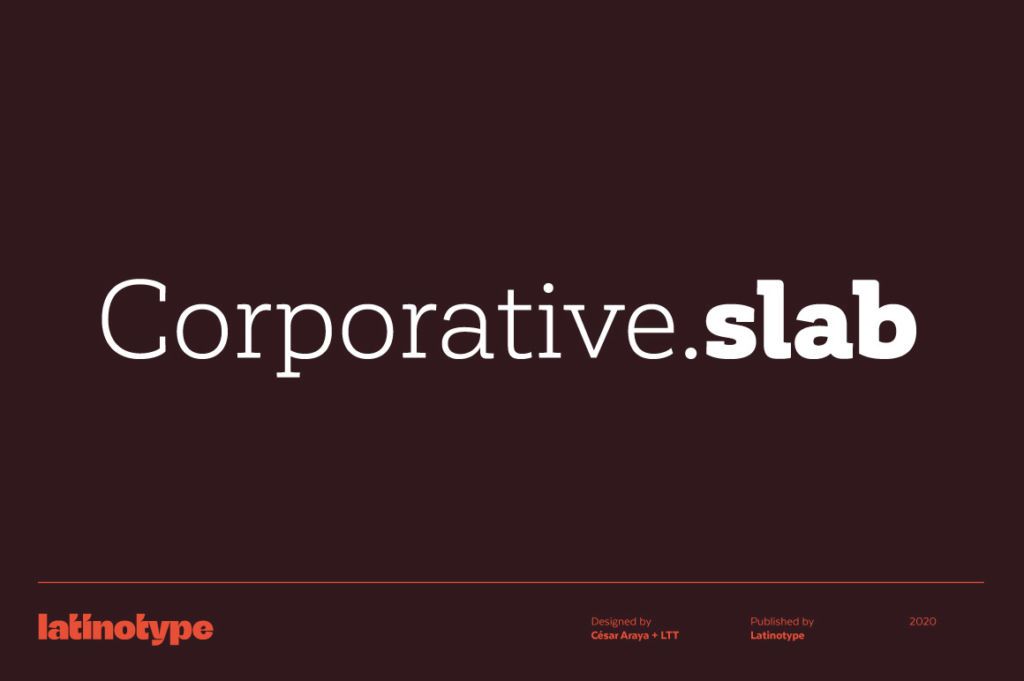
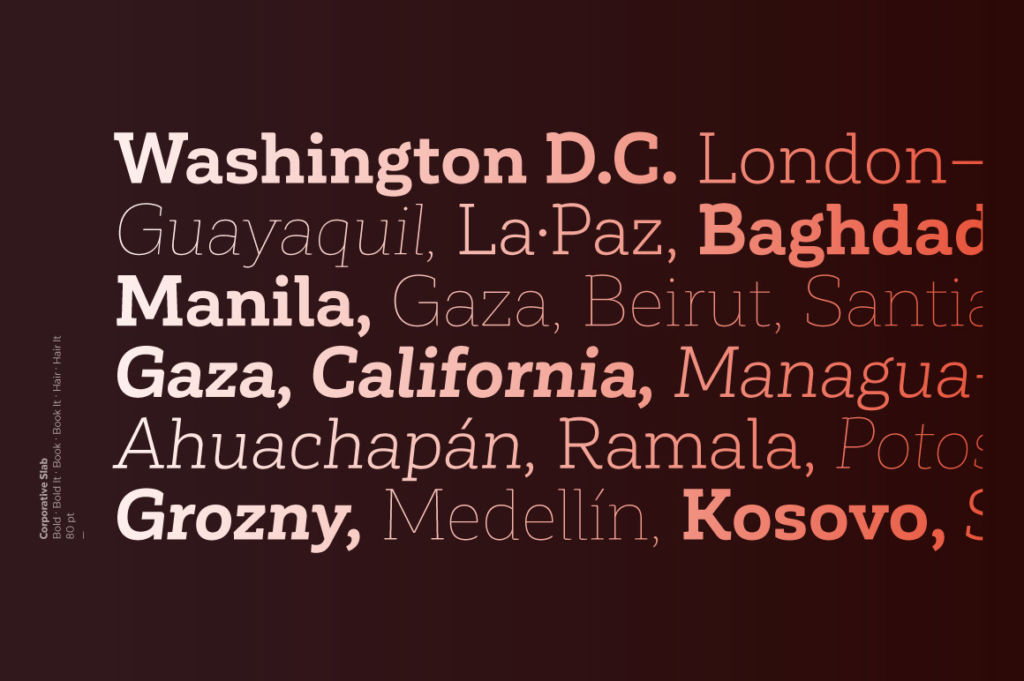
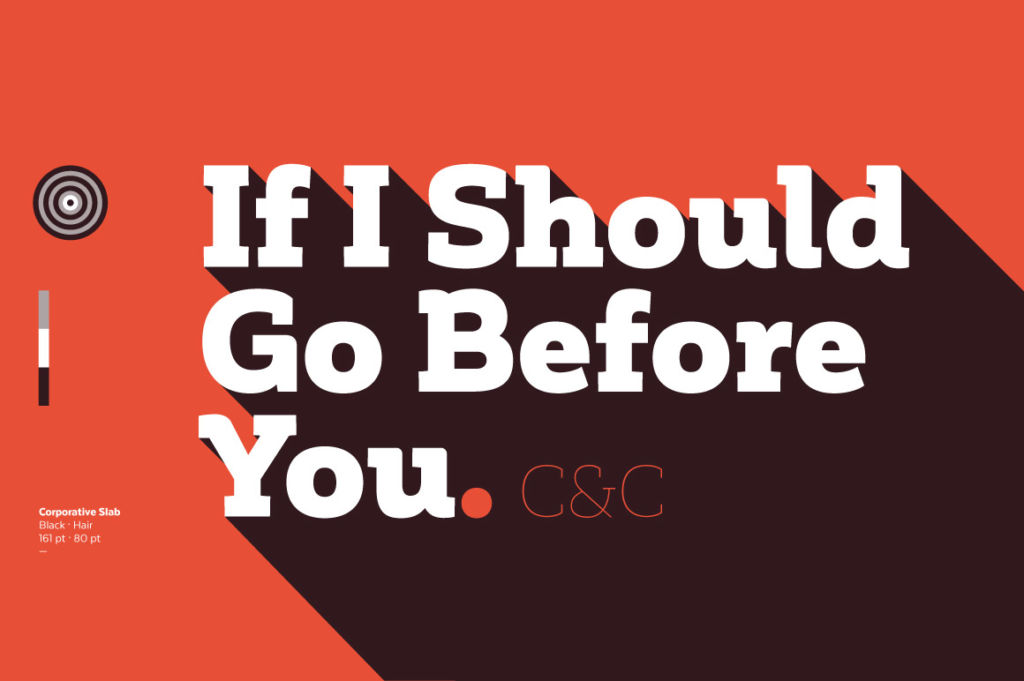
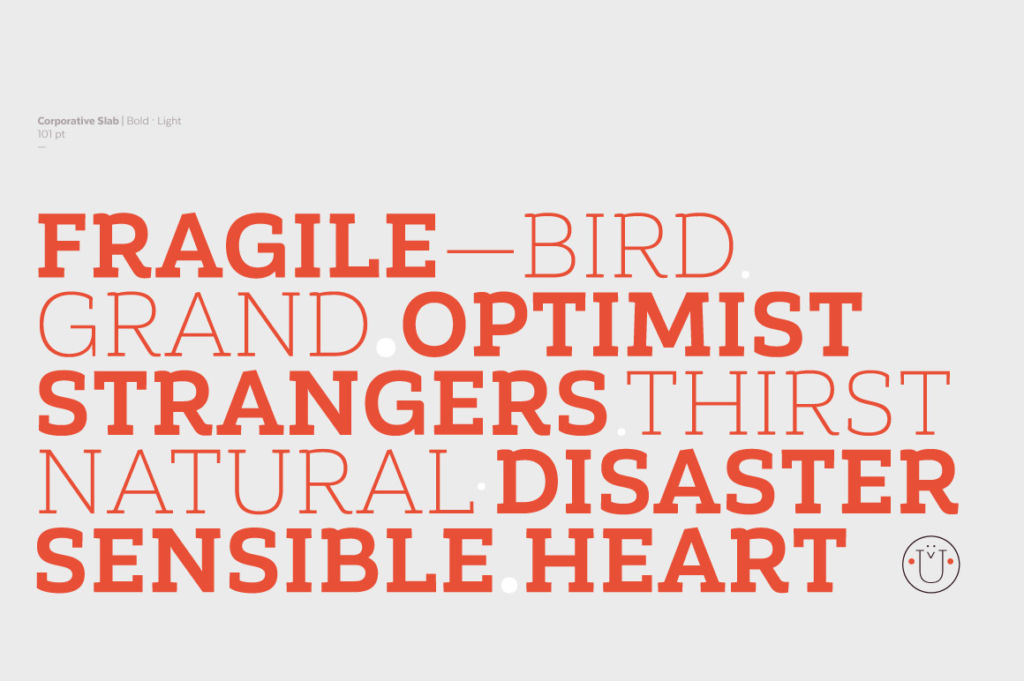
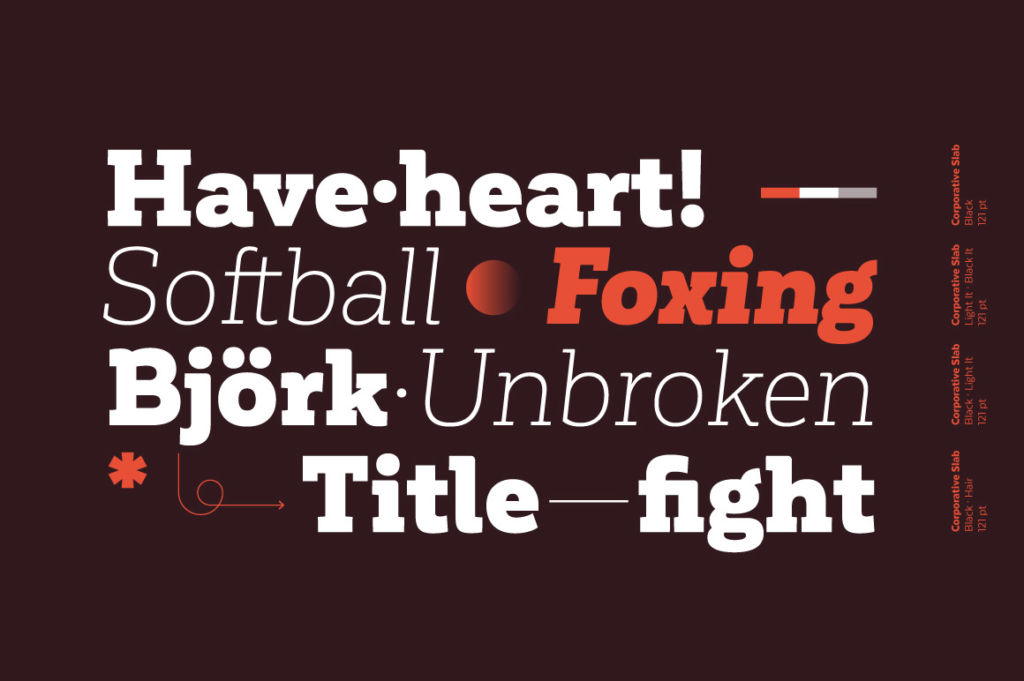
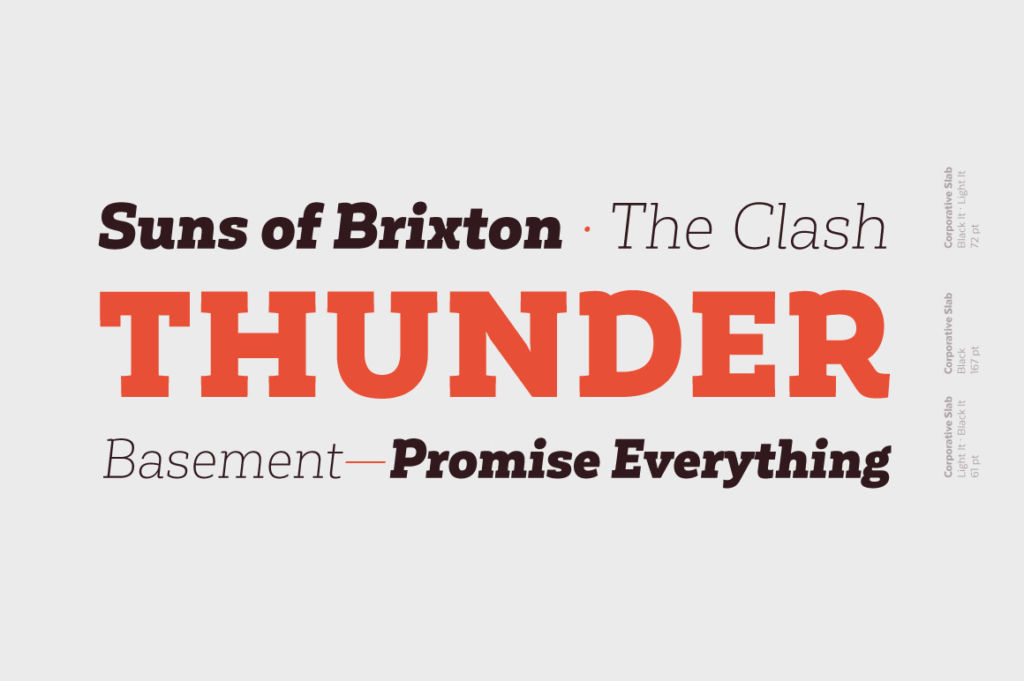
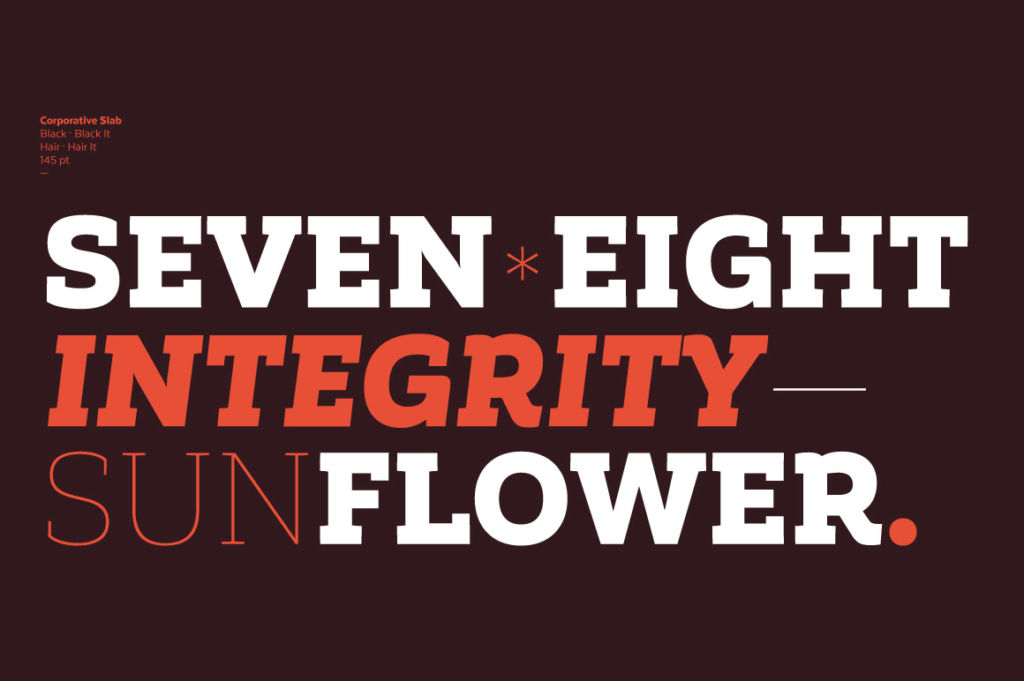
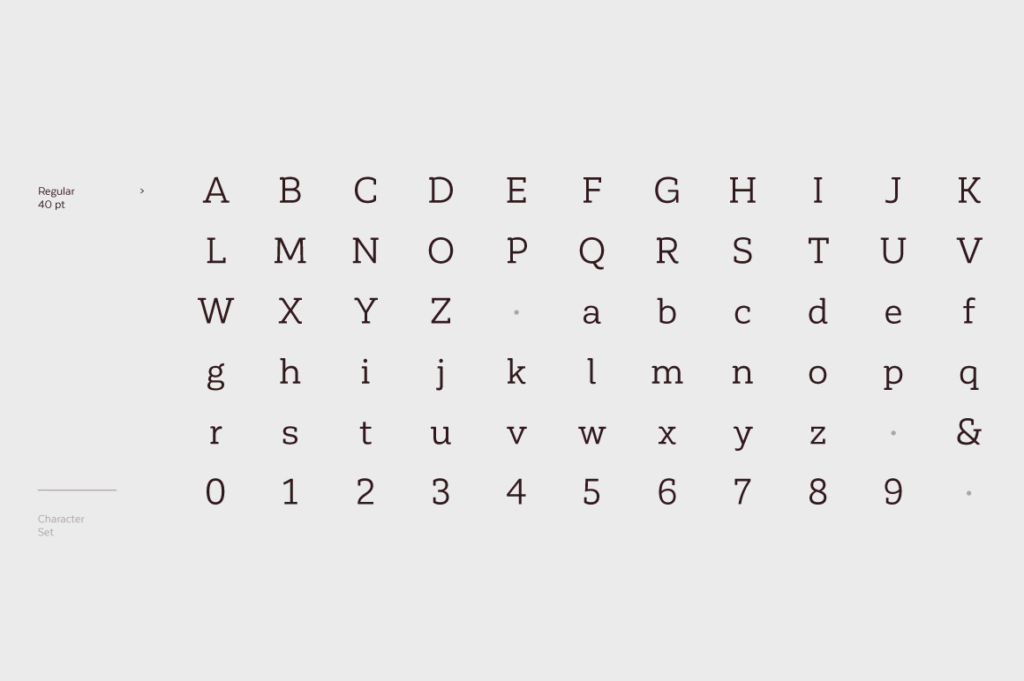
豊富なウェイトで選択肢が豊富なセリフフォント:GABRIELA
4書体それぞれに9種類のウェイトを収録したセリフフォント「GABRIELA」。デザインに合わせて、様々なウェイトを使い分けられます。
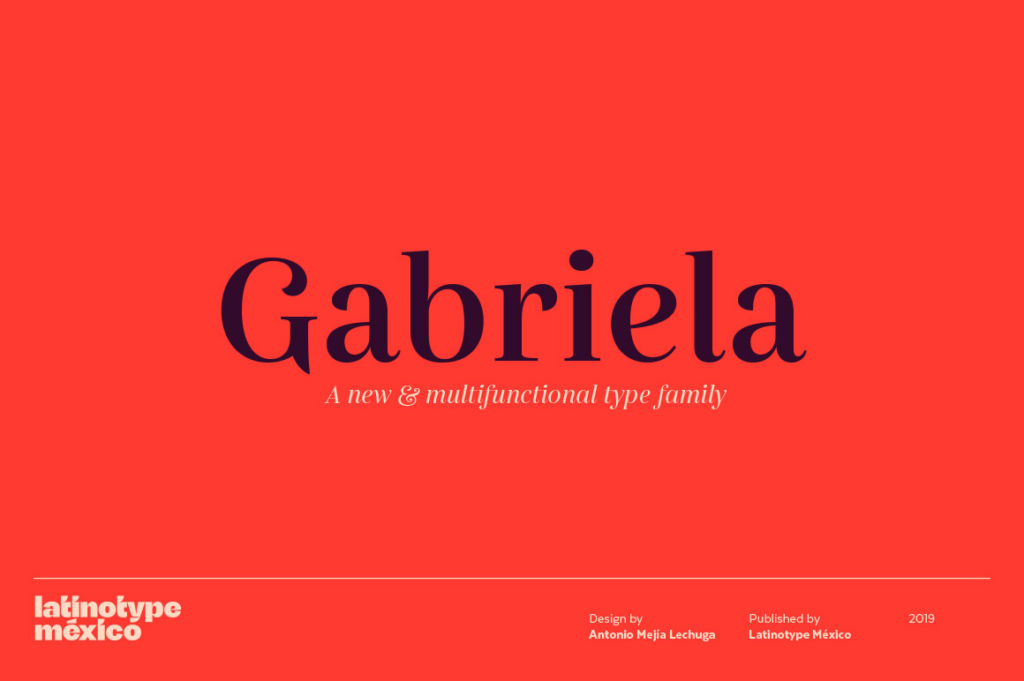
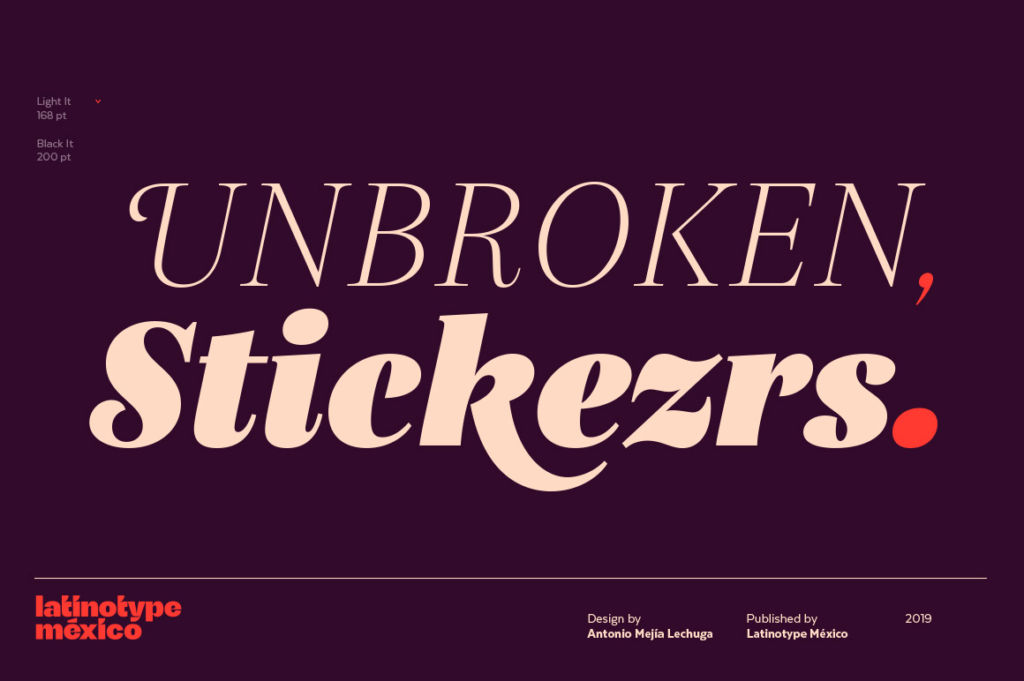
ステンシル風のデザインセリフフォントも収録:BW DARIUS
ステンシル・レギュラー・イタリックそれぞれ4種類のウェイトをおさめたセリフフォント「BW DARIUS」。デザインのアクセントに活躍しそうなステンシル体に注目です。
流行に左右されずに使えるタイムレスなセリフフォント:ZEIT
流行に左右されることなく使える、タイムレスなフォント「ZEIT」。合字のデザインもユニークで、本文組みからロゴ制作まで多様なニーズに対応できます。